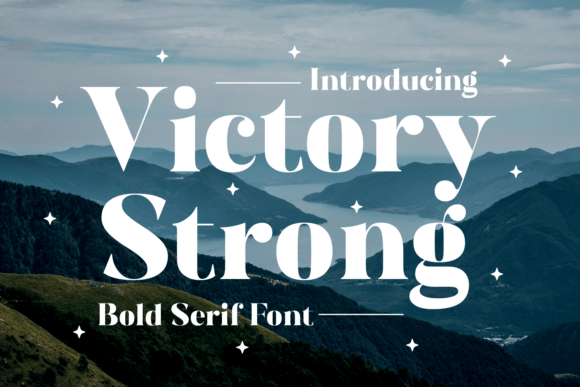
Victory Strong
Victory Strong์™€ ๊ฐ™์€ ๊ณ ํ’ˆ์งˆ ์ž์‚ฐ์„ ์ฐพ๊ณ  ์žˆ๋‹ค๋ฉด ์ด ํ”„๋ฆฌ๋ฏธ์—„ ํŒจํ‚ค์ง€๋Š” ์ฐฝ์˜์ ์ธ ํ”„๋กœ์ ํŠธ๋ฅผ ์œ„ํ•œ ํ™˜์ƒ์ ์ธ ์„ ํƒ์ž…๋‹ˆ๋‹ค.
POD(์ฃผ๋ฌธํ˜• ์ธ์‡„) ์ œํ’ˆ, ๊ฒฐํ˜ผ์‹ ์ดˆ๋Œ€์žฅ ๋˜๋Š” ์†Œ์…œ ๋ฏธ๋””์–ด ๊ทธ๋ž˜ํ”ฝ์„ ๋งŒ๋“ค ๋•Œ Victory Strong๋Š” ์ด์ƒ์ ์ธ ์„ ํƒ์ž…๋‹ˆ๋‹ค.